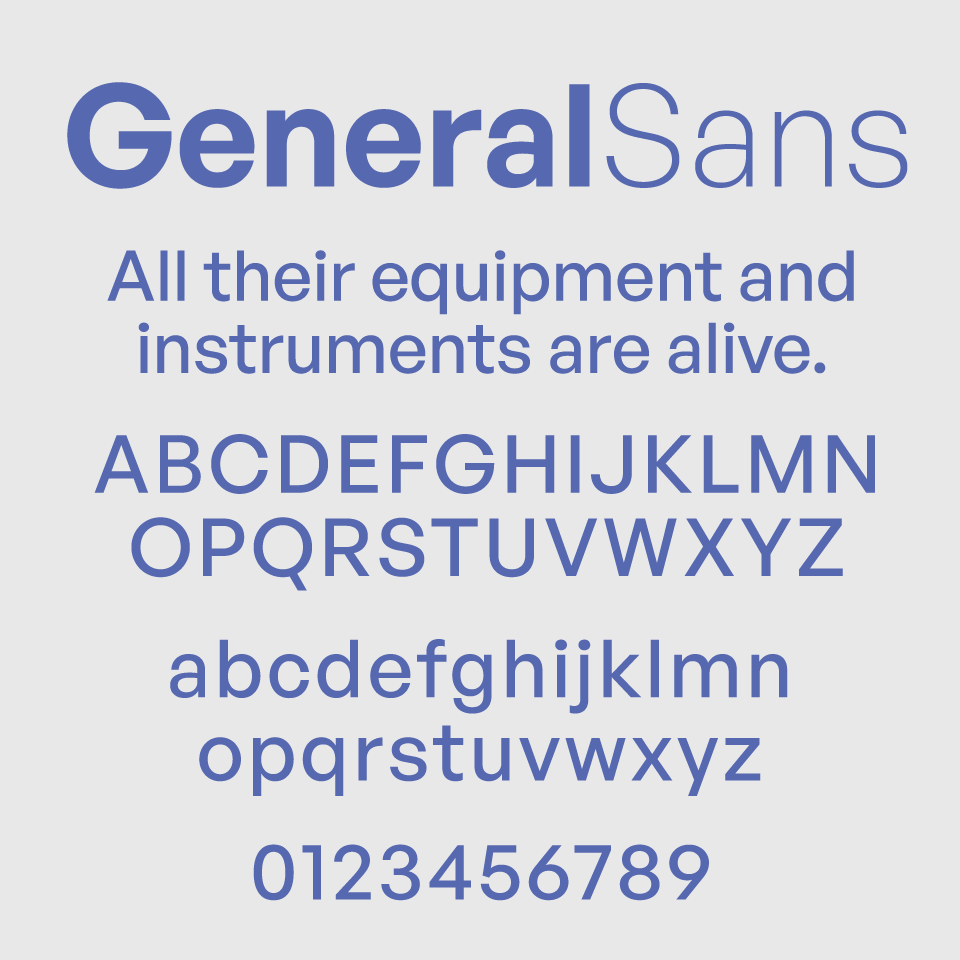
General Sansは、現代的で洗練されたサンセリフフォントです。やや広めの字幅と自然な丸みが、堅すぎず砕けすぎない絶妙なバランスを保っており、読みやすく汎用性の高い書体です。
無機質になりすぎないナチュラルな印象があり、ビジネスやテック系、UIデザインなどでも幅広く活躍します。堅実でありながらもやわらかさを持ち合わせた、12種類のスタイルをもつ安心して使える現代的なフォントです。